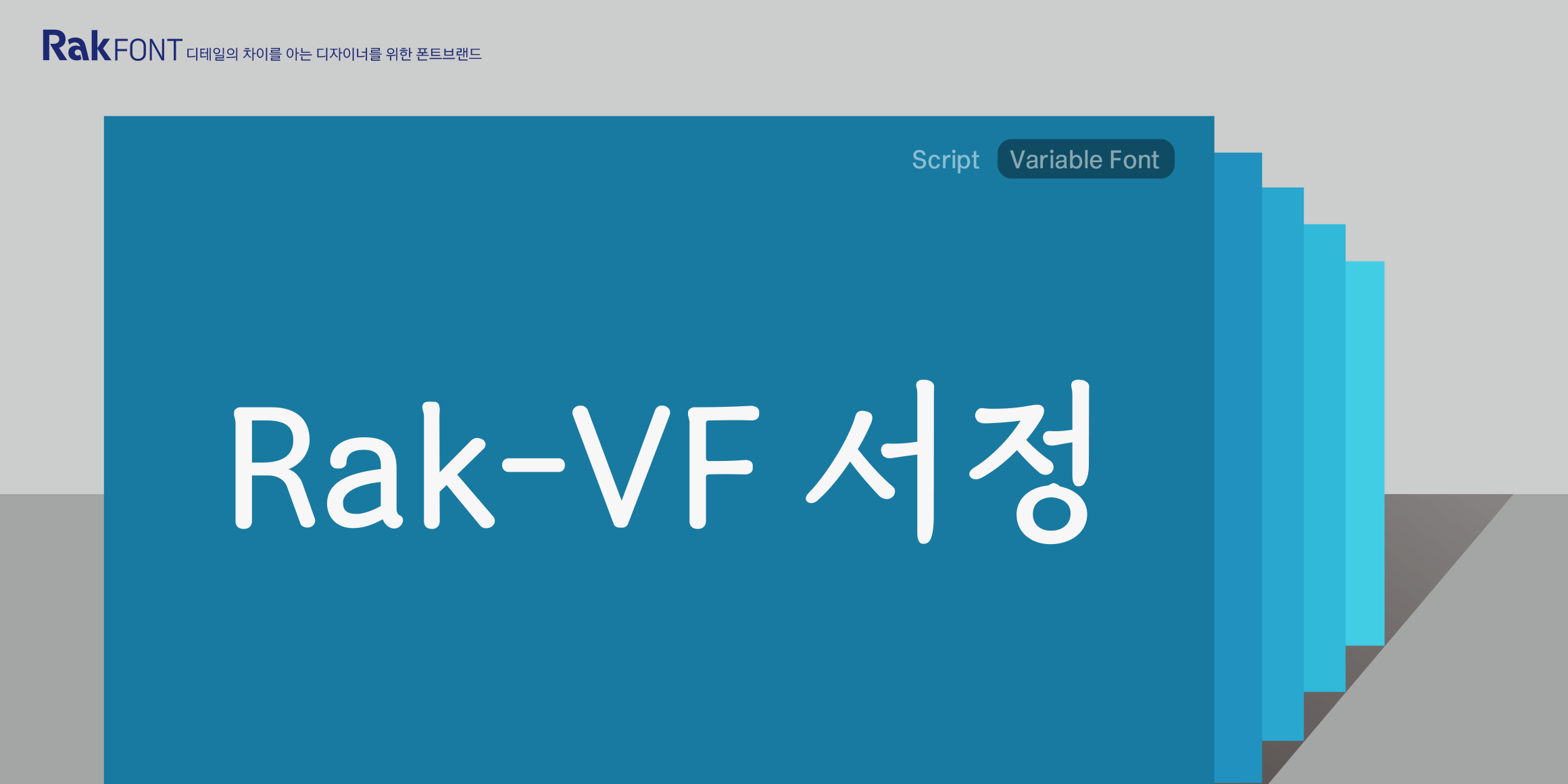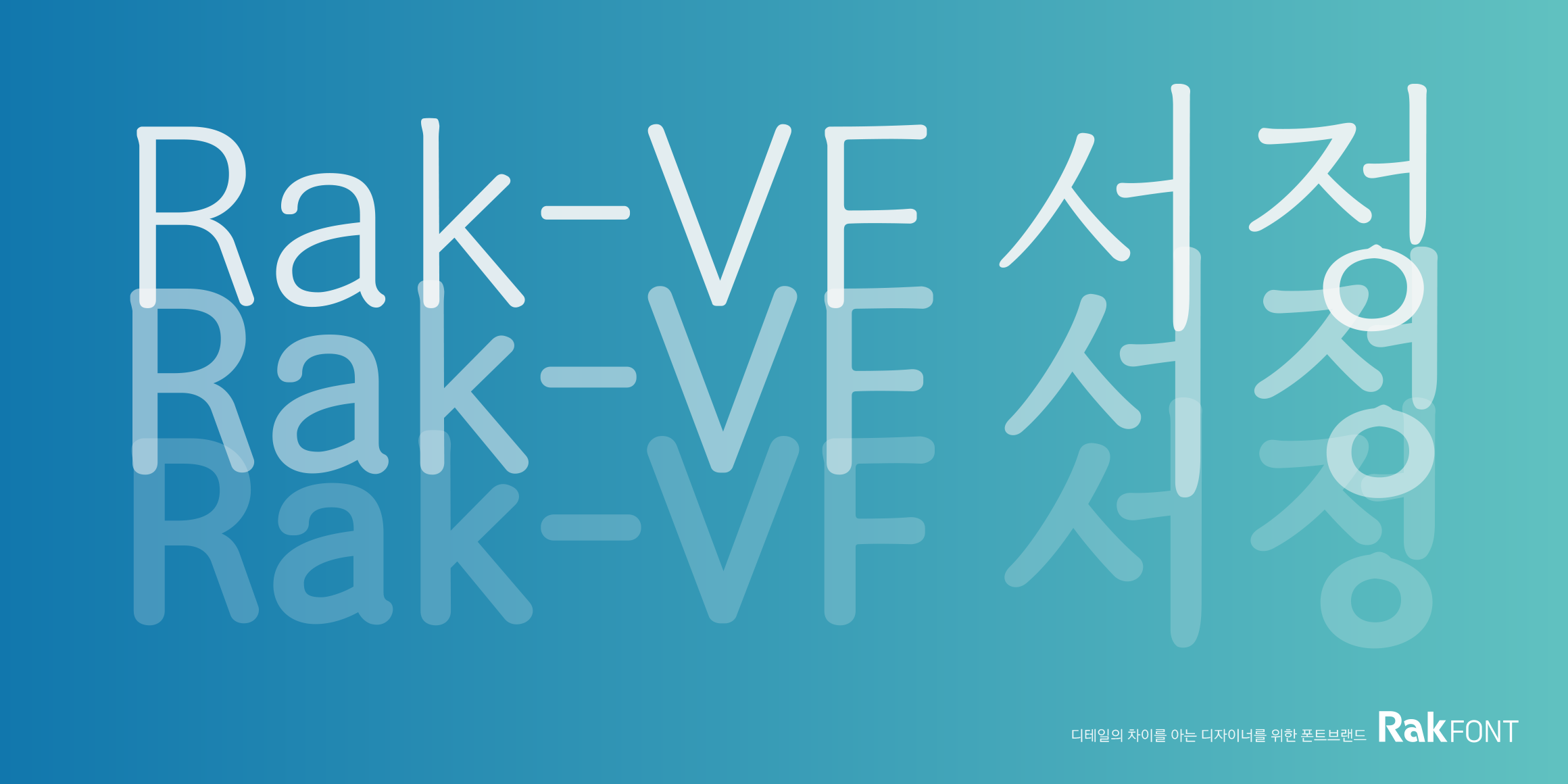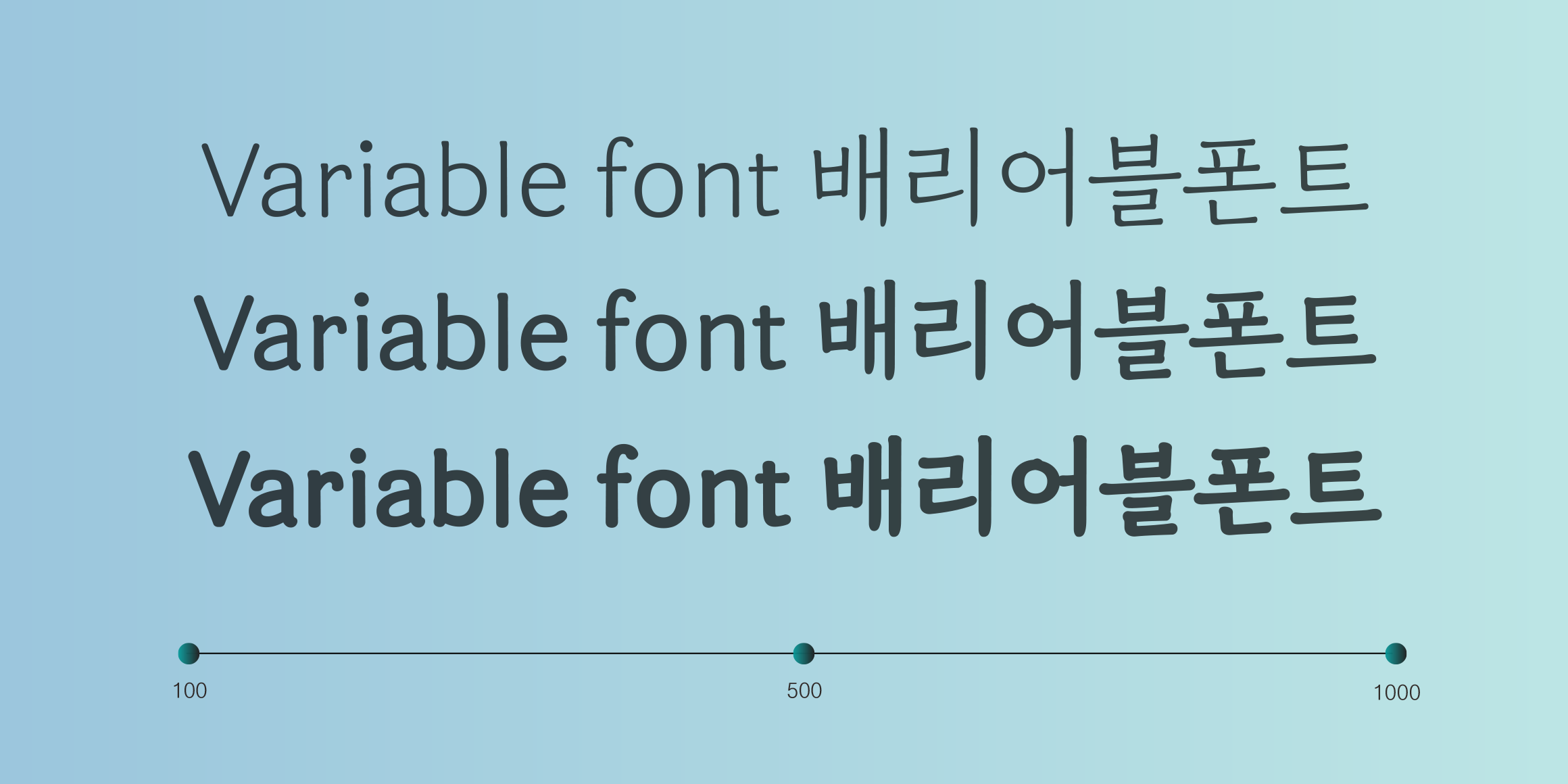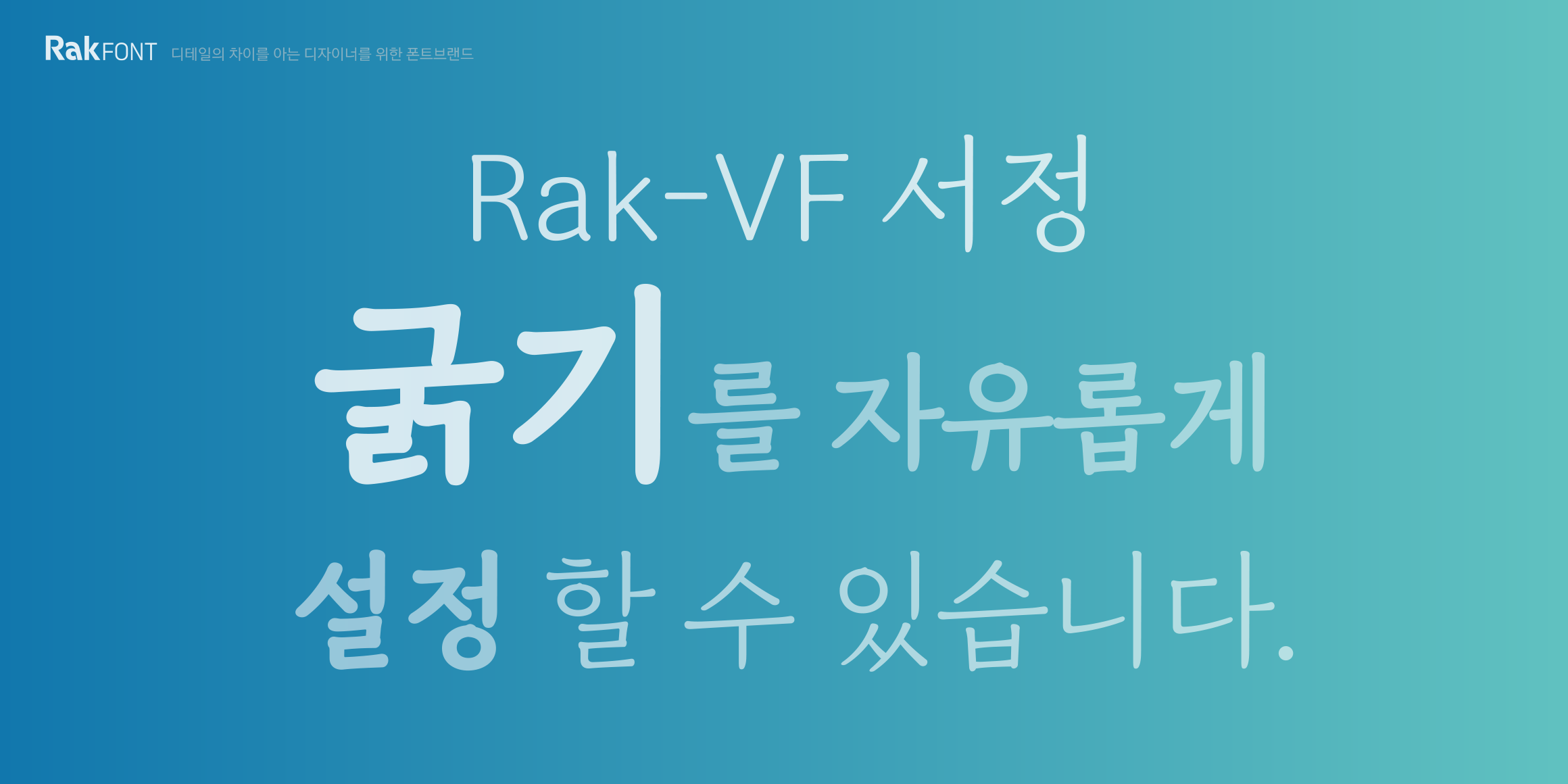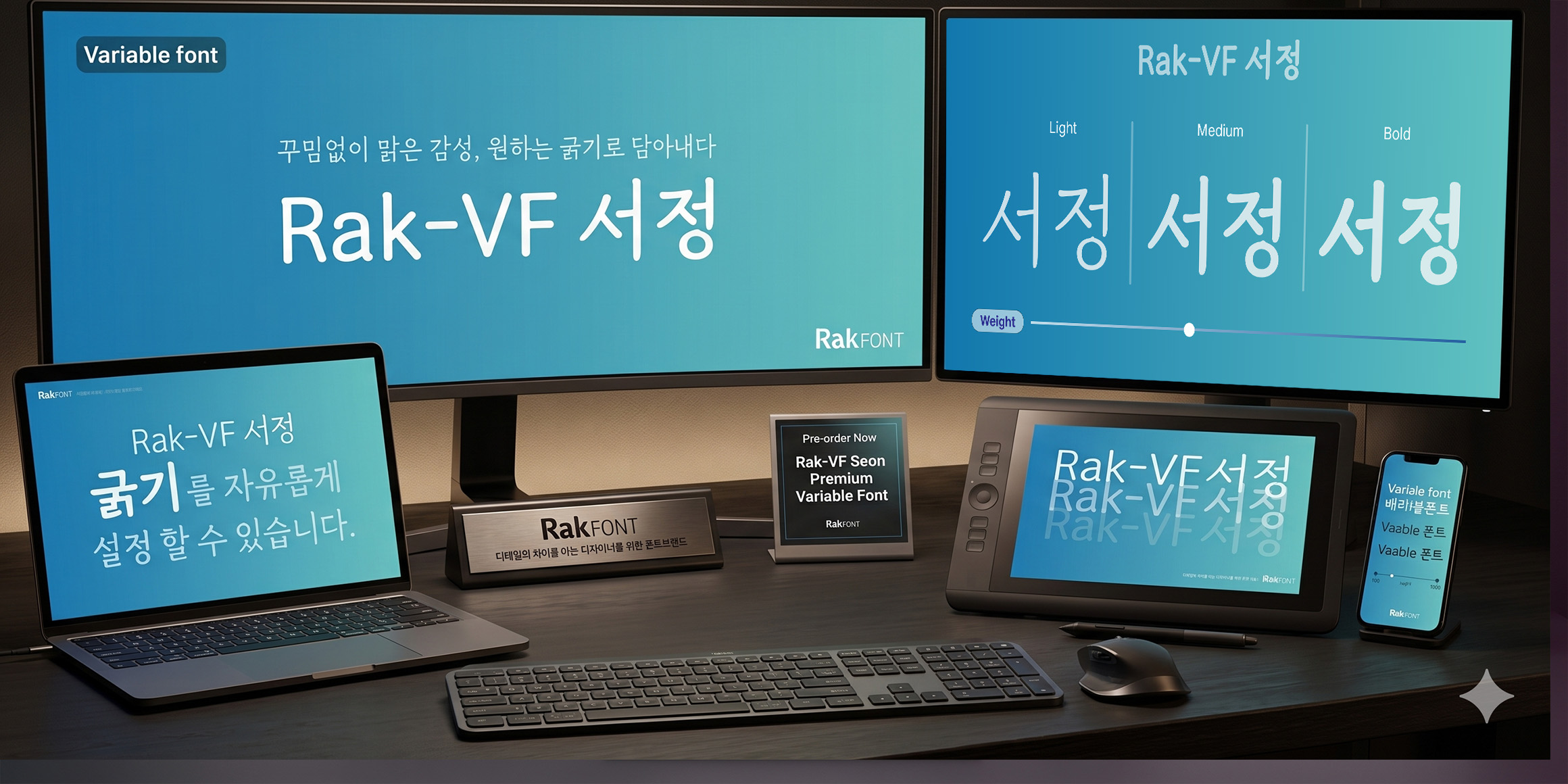
Rak-VF 서정
Rakfont
'Rak-VF 서정'은 꾸밈을 절제한 담백한 손글씨의 감성에 배리어블(Variable) 기술을 결합한 서체입니다. 오리지널 Rak서정이 가진 자연스럽고 여유로운 무드는 온전히 유지하면서, 웨이트(Weight) 축을 무한하게 확장하여 사용자가 원하는 모든 굵기에 완벽하게 대응합니다. 1%의 미세한 두께 변화로 텍스트의 감도를 정교하게 조율하고자 하는 하이엔드 디자이너에게 최적의 솔루션을 제공합니다.
• 박용락
• Rak-VF 서정 / Rak-VF SeoJung